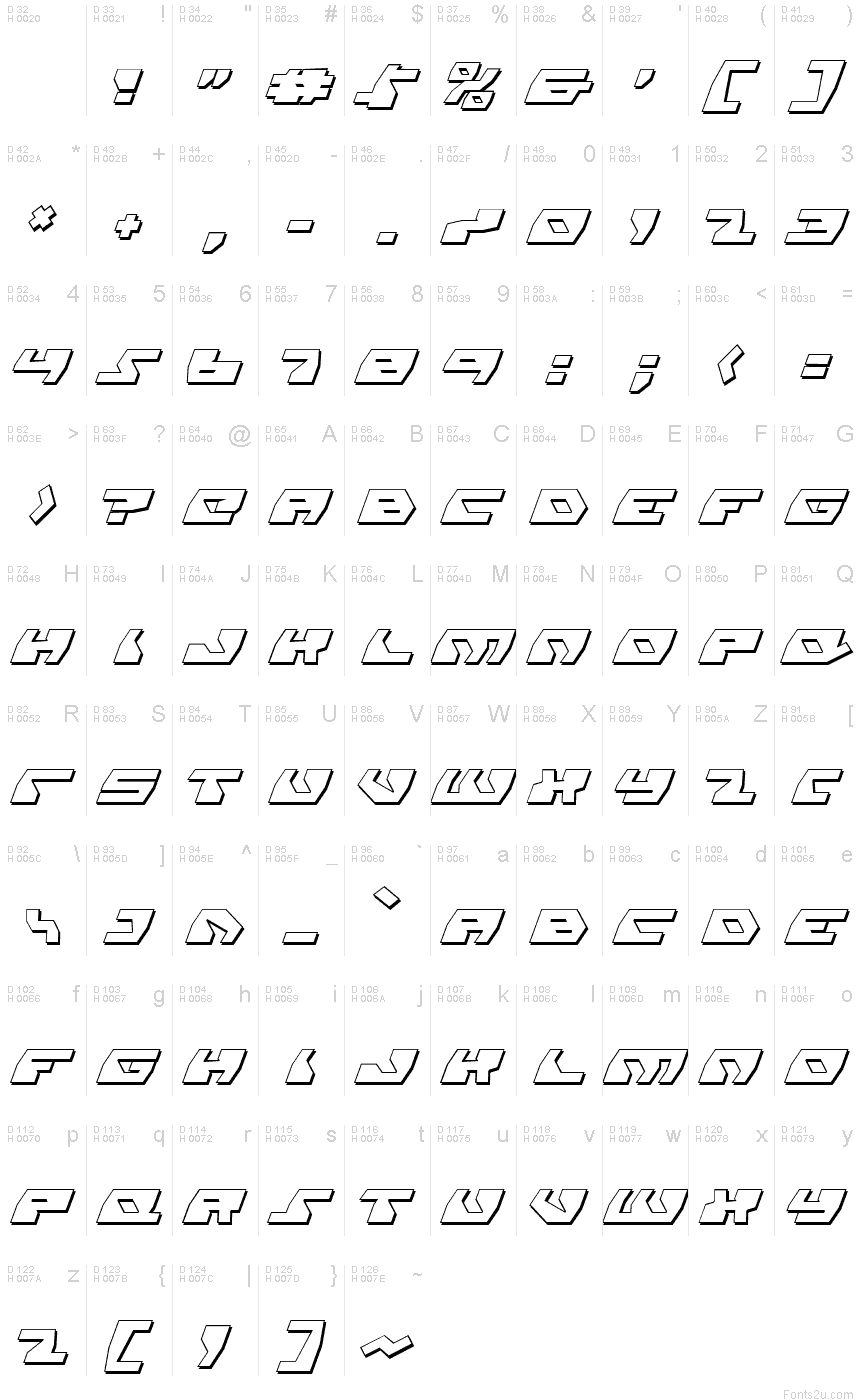
Daedalus Shadow Italic od Iconian Fonts to darmowy krój displayowy w stylu techno z wyraźnym zacięciem sci-fi. Litery wyglądają na pancerne i aerodynamiczne, zbudowane z masywnych, kanciastych form z konsekwentnym cieniem offsetowym, co nadaje całości śmiały klimat arcade i komiksowej przyszłości.
Świetnie sprawdza się w logo gier, grafikach esportowych, tytułach na plakatach, okładkach soundtracków i planszach tytułowych, gdzie wysunięty cień wykonuje całą ciężką pracę. Jako darmowy font, sprawdzi się również w krótkim brandingu, monogramach i nagłówkach, które potrzebują dynamiki bez zbędnych ozdobników, ponieważ diagonalne ustawienie i fasetowe narożniki tworzą wystarczająco mocny efekt.
Daedalus Shadow Italic
Dan Zadorozny